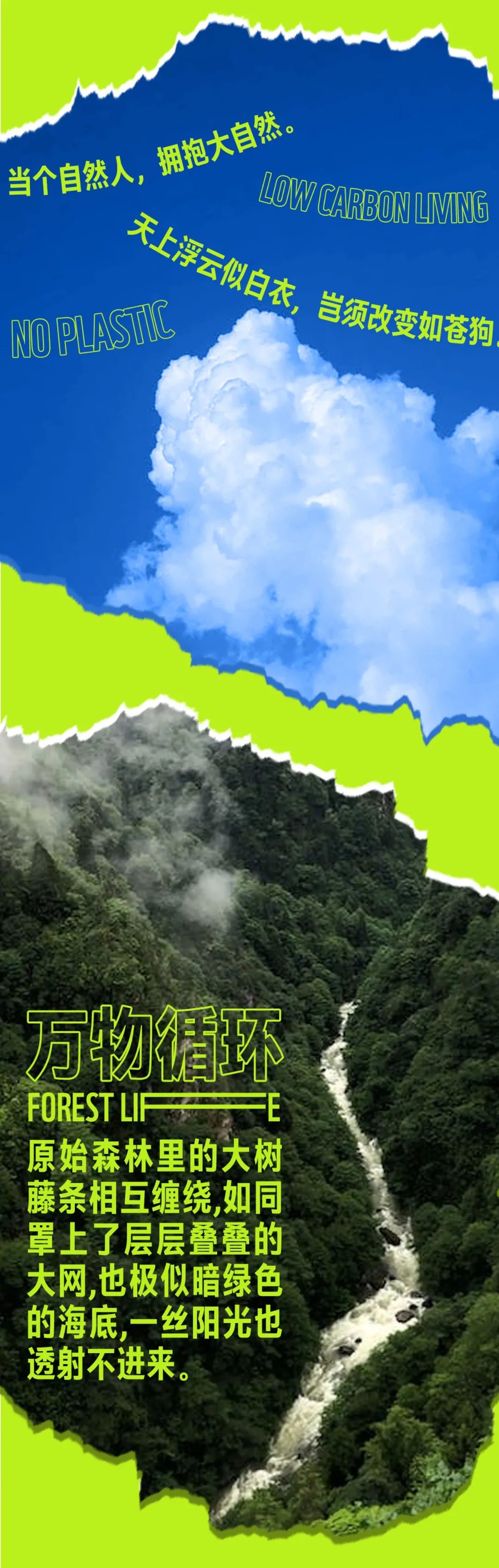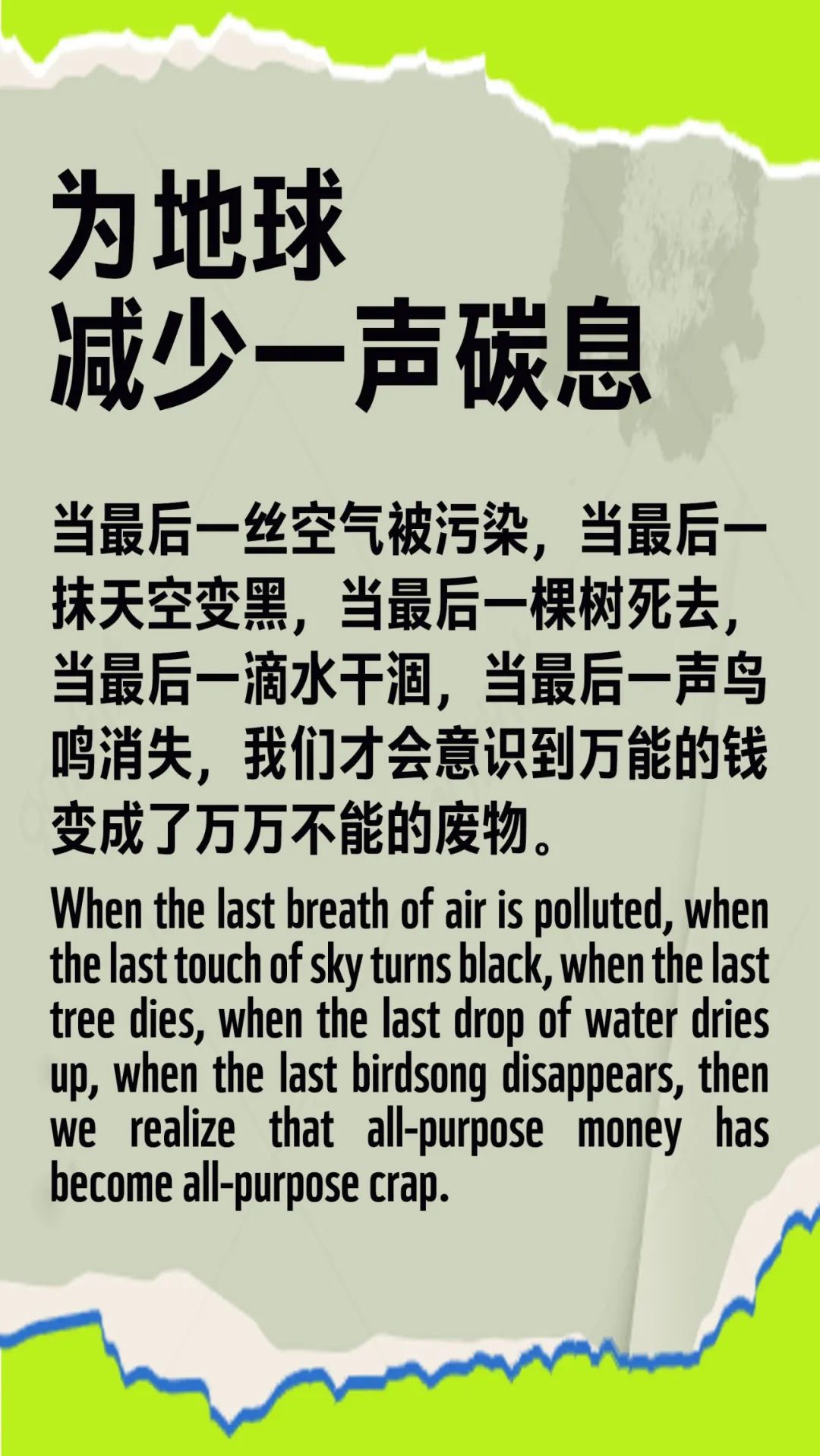
字体推荐Aa星球黑|世界地球日,与世界同频呼吸
字体推荐Aa星球黑|世界地球日,与世界同频呼吸,这款字体结构工整、笔画清晰,兼顾美观与易读性,适用于标题、正文、海报、包装、LOGO 等多种场景。字形优雅稳定,风格百搭耐看,适配日常排版与创意设计,让文字呈现更舒适、更具质感。字体推荐Aa星球黑|世界地球日,与世界同频呼吸一笔一画,皆是细节,以均衡的比例、流畅的线条打造舒适视觉体验,字形端正大气,风格简约现代。无论是商业设计、品牌宣传还是日常排版,都能轻松驾驭,让文字更有格调与力量。字体推荐Aa星球黑|世界地球日,与世界同频呼吸字体下载。
Aa星球黑世界地球日 (TheWorld Earth Day)每年的4月22日,是一个专门为世界环境保护而设立的节日,旨在提高民众对于现有环境问题的认识,并动员民众参与到环保运动中,通过绿色低碳生活,改善地球的整体环境。
字体窄于常规字形,相较之下,在有限的空间内能排列出更多的字符,从而表达出更多的信息,字体依据轴线完美对称,以简洁的线条表现,体现出秩序、和平、均衡的经典美